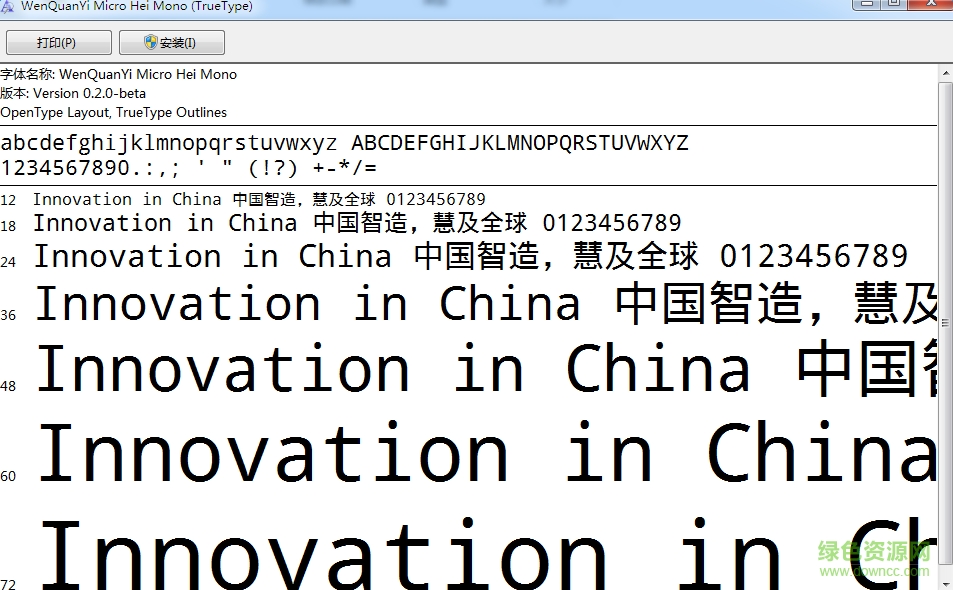
文泉驛等寬微米黑是一款黑體電腦字體,在求保持傳統(tǒng)的黑體風(fēng)格與結(jié)構(gòu)方正,筆形規(guī)范實用的同時,點(diǎn)形到撇、捺形都做了大膽的創(chuàng)新,使得該字體更加適合用于設(shè)計領(lǐng)域,喜歡就來綠色資源網(wǎng)下載!
文泉驛等寬微米黑是一款黑體字體,與傳統(tǒng)黑體相比更加強(qiáng)調(diào)了黑體的特征,筆畫簡潔、硬朗更穩(wěn)重大方;字形結(jié)構(gòu)方正、端莊,橫豎筆畫挺拔,軟筆畫細(xì)膩、柔美,使得該字體相較于原黑體更富有藝術(shù)感!